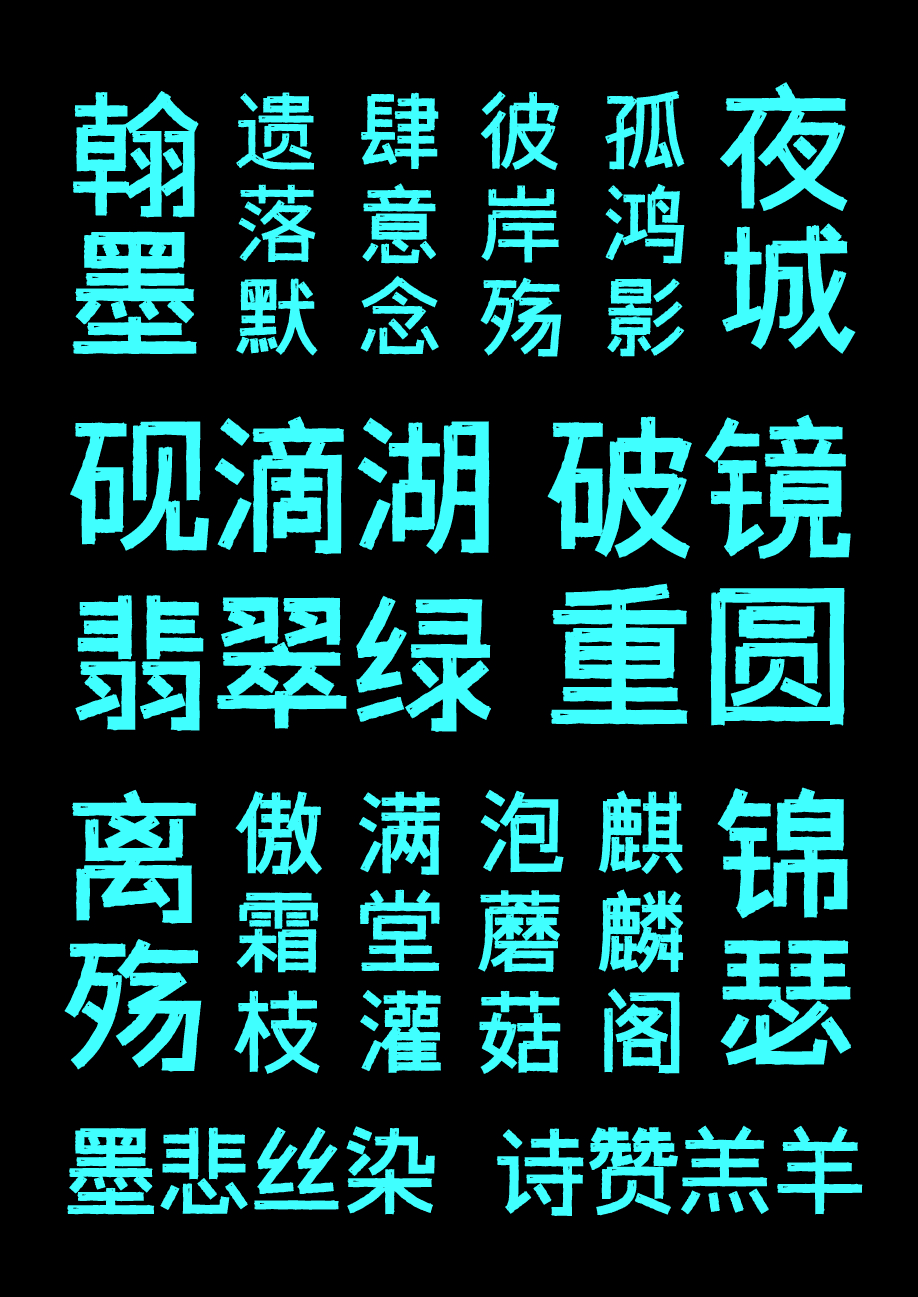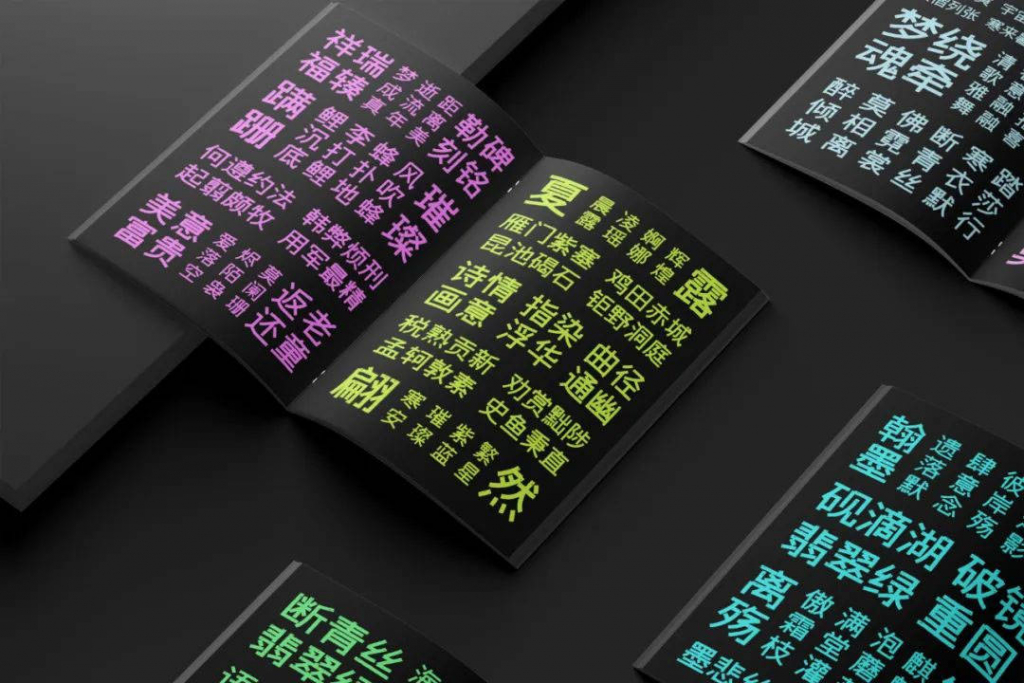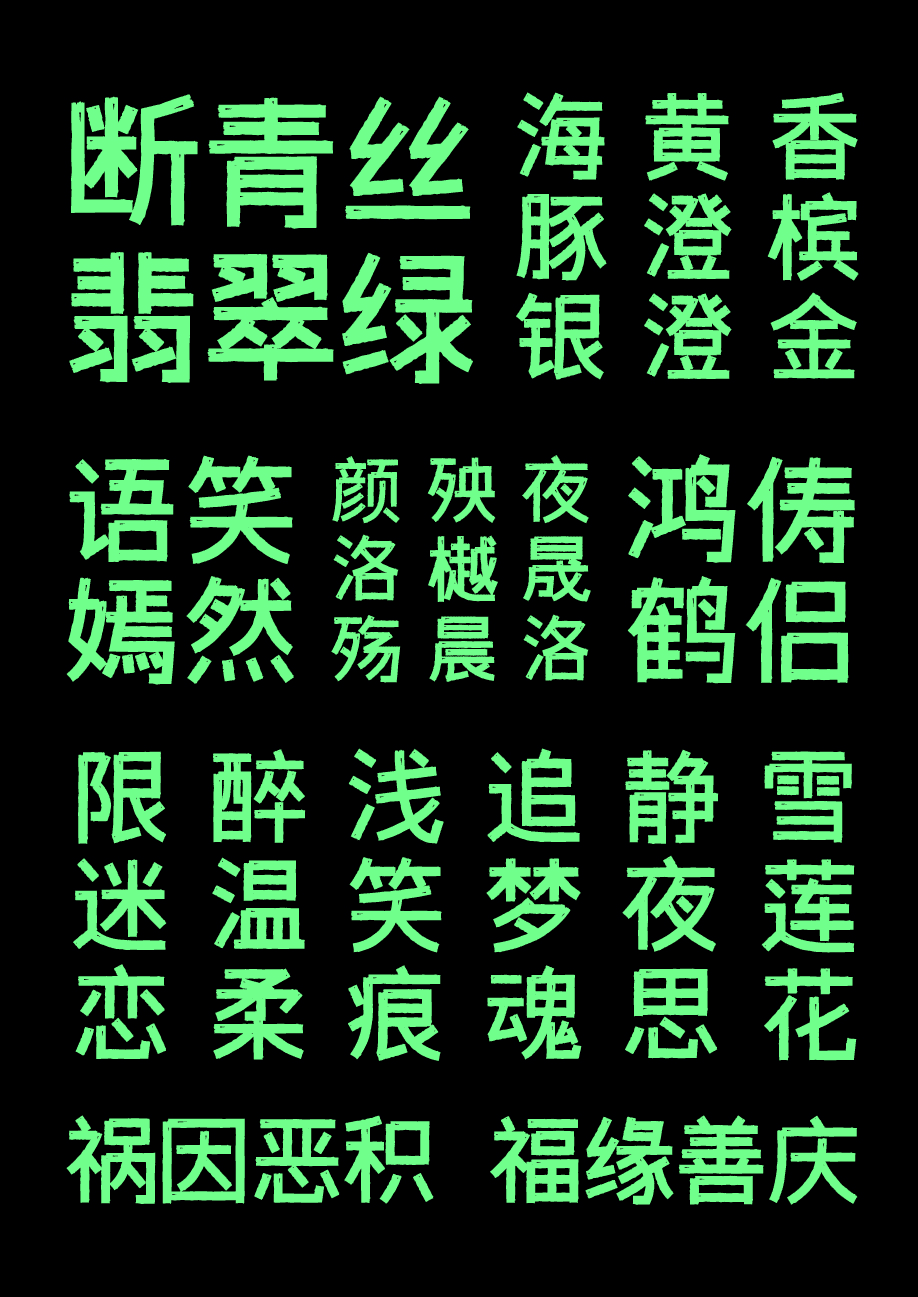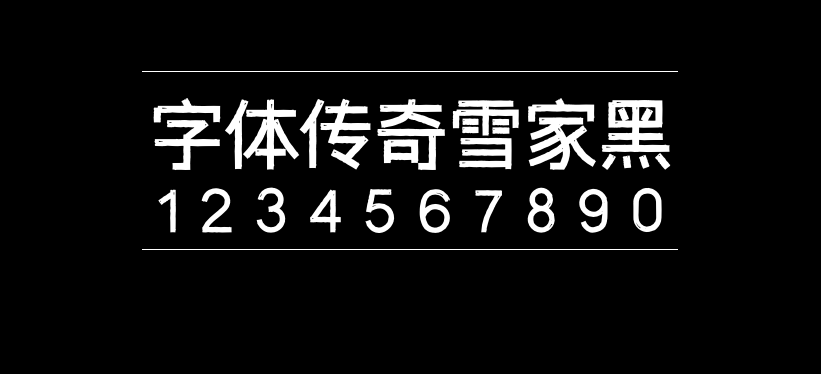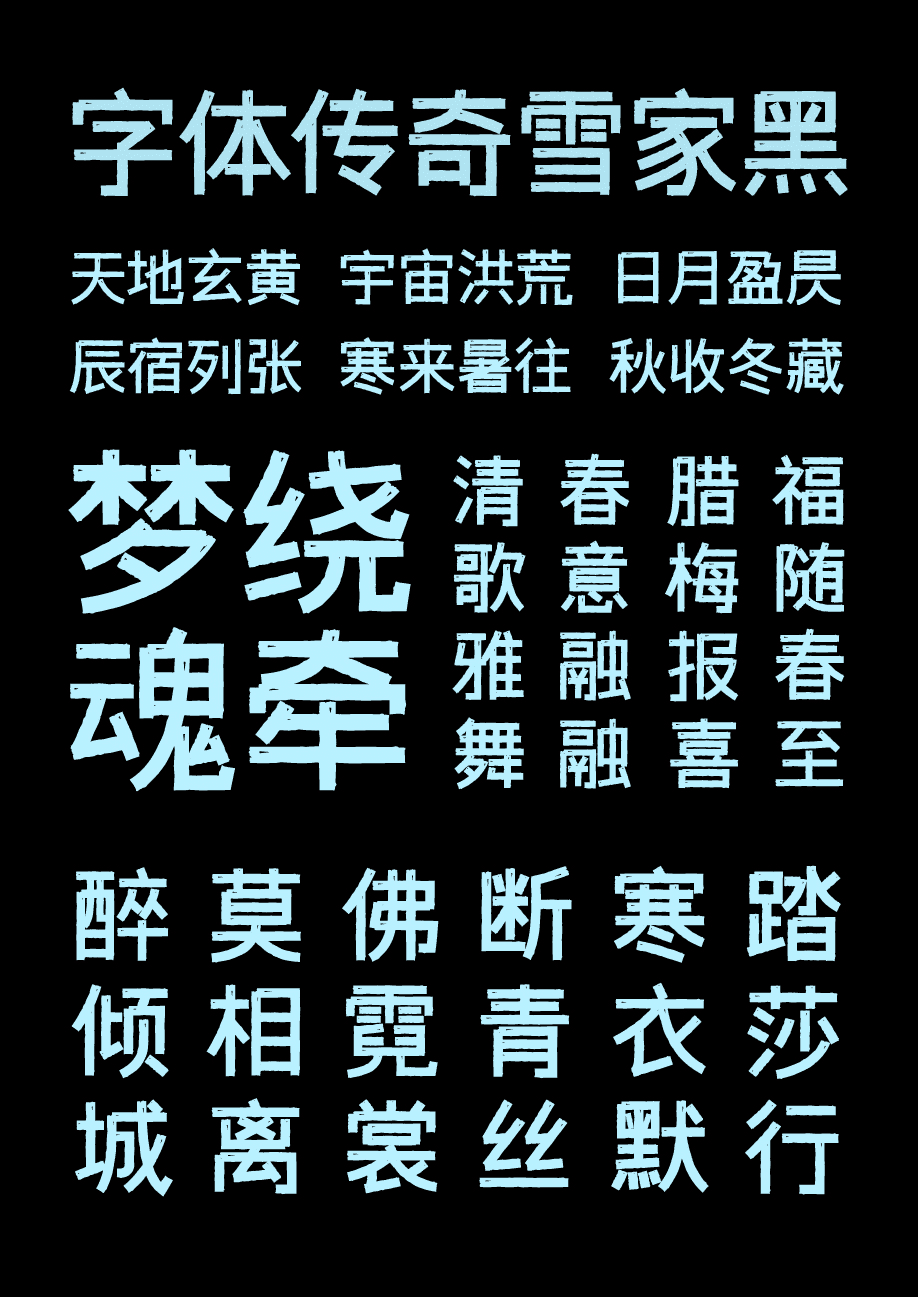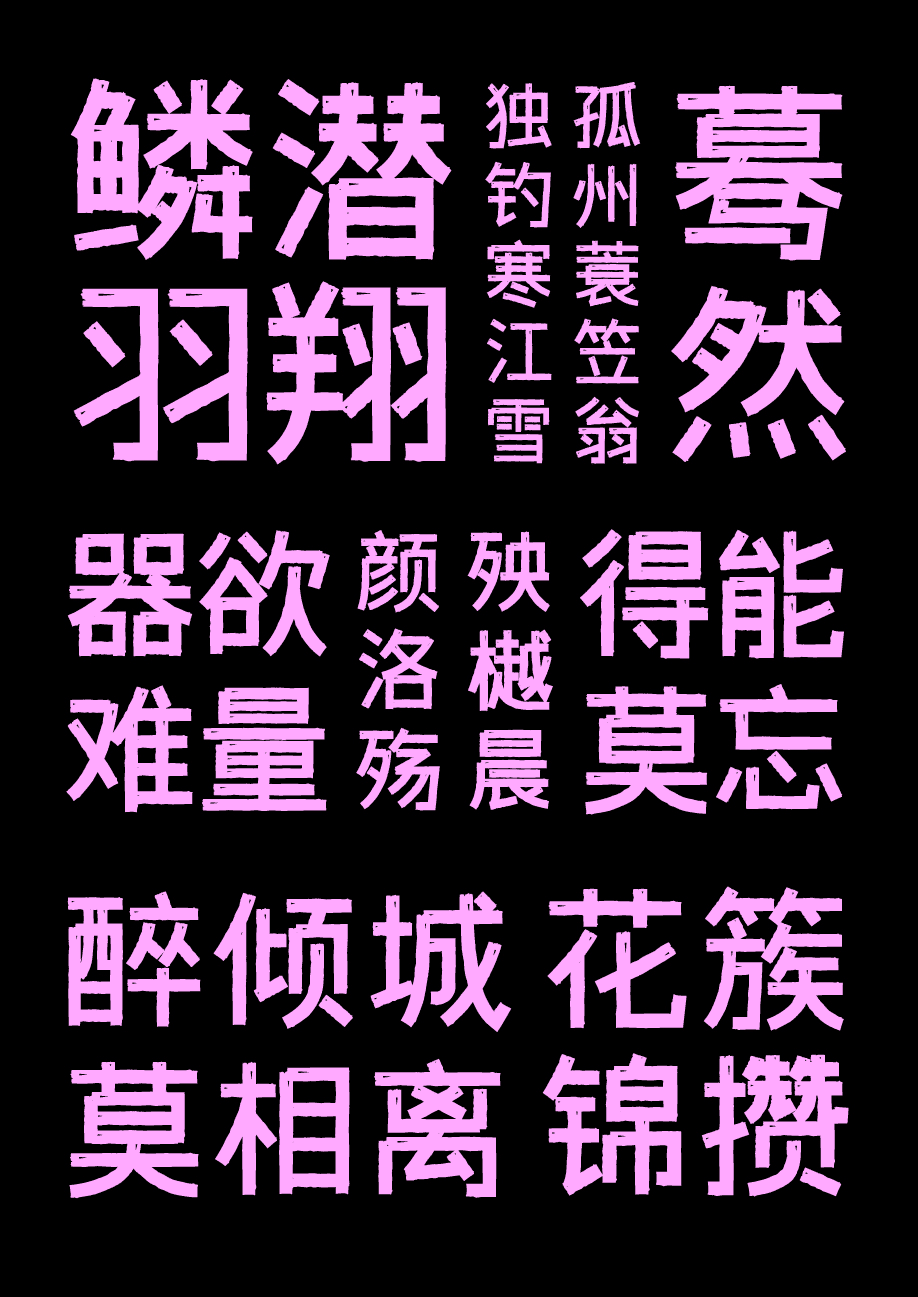
字体传奇雪家黑
字体传奇雪家黑是由张家佳字库团成员郭小雪设计,字库命名由他的名字和家乡张家口组合,雪家黑,这款字体结构根据黑体进行设计,笔画复古元素装饰应用。
字体故事:大家好,我叫郭小雪,我是一名坐标上海的设计师。一直以来,渴望出一套个人字体产品。也是首套免费商用产品。由于工作项目原因,这款字体是晚上,周六日时间来做。效率还是不高的。
有时候也会拖延,断断续续,真正加快研发的速度是上海疫情居家时间,有独立时间全力做字库研发。在研发字库中得到张老师的很多指导建议。
字库之路需要专注度、时间投入、精力投入、坚持,不然就会轻易放弃。一个人的渴望和喜好和专注程度非常关键。今后的数字产品之路会更加努力,研发出更多好的产品。